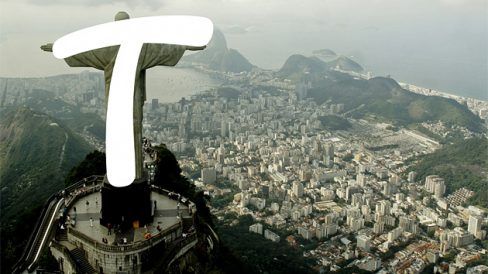
Comitê revela a tipografia dos Jogos Olímpicos Rio 2016
O Comitê Organizador dos Jogos Olímpicos e Paralímpicos Rio 2016 revelou recentemente a fonte que será parte da identidade visual do evento no Brasil. A criação do estúdio Dalton Maag levou oito meses de trabalho, desenvolvendo 5.448 caracteres no total.
Inspirado pelo logo, o conceito tipográfico também remete a diversos elementos da cidade do Rio de Janeiro. O calçadão de Copacabana, por exemplo, está presente nas letras “m” e “n”. A letra “r” remete a Pedra da Gávea, e por aí vai.
Numa primeira olhada, agrada. E analisando cada detalhe, posso dizer que o  projeto foi muito bem concebido. Não se trata apenas de uma “fonte com cara disso ou daquilo”. Ela possui tudo o que um tipo sério necessita. Boas ligaduras (adorei a do s+a em especial), ótima legibilidade e o principal: A cara do Rio de Janeiro.
É despojada, artística e aconchegante. Desde a primeira vez que vi (cheguei a postar aqui) a criação da Tátil, soube que aquilo era só o começo.